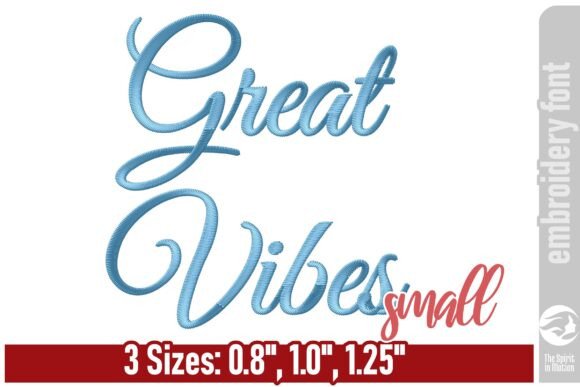
Great Vibes Script Embroidery Font
Được chế tác với độ chính xác cao, Great Vibes Script Embroidery Font cung cấp các vector sạch, kiểu chữ mượt mà và giấy phép thương mại để bạn yên tâm.